蒙纳字库不知道各位是否熟悉,这是目前比较热门的一系列电脑字体,得到了众多用户们的认可,个人也比较依赖这一系列字体,看起来非常不错,而且选择面比较广,可能很多朋友对此并不是特别熟悉,所以下面就带各位了解一下蒙纳中文字库这方面内容,同时再来看一下蒙纳中文字库有哪些经典的特色。
蒙纳中文字库是目前比较独特的字体库之一,很多朋友都特别喜欢,不仅仅可以免费使用,而且还非常简洁大方,字体种类也比较多,可以用到各种设计创作中,可以凸显出个人的特点,把一些文字信息变得更有特色,而且画面看起来也会更美观,目前来看这一系列产品都是很不错的,不知道大家是否感兴趣呢?
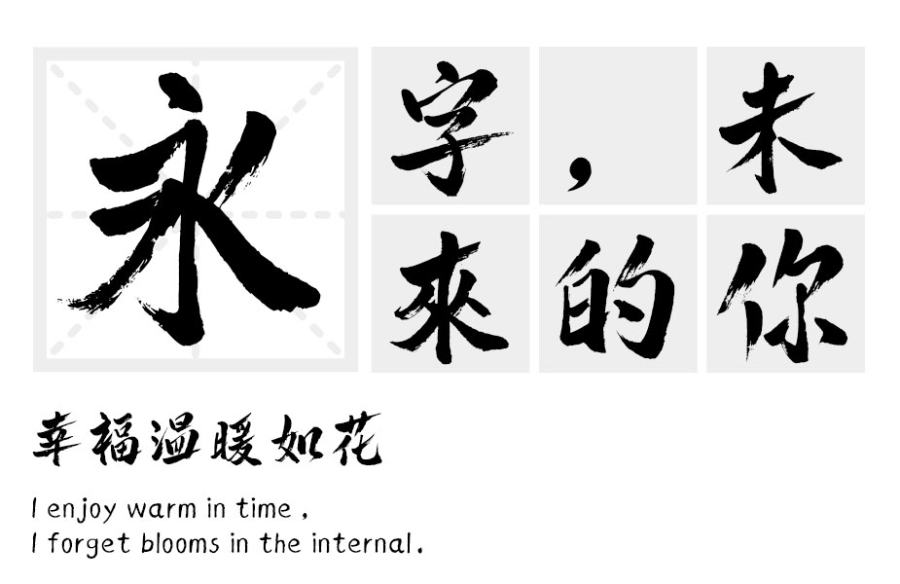
蒙纳中文字库种类是非常多的,可以用于各种方面,同时这一类字体非常端庄,看起来还挺美观的,效果也特别统一,更主要的是这一个字库里面的所有字体都很完整,可以运用到各种领域,大多数的朋友都特别喜欢,不仅名片设计里可以用,而且还可以放在海报影视制作等一些各种用字领域,感兴趣的朋友可以去免费下载。